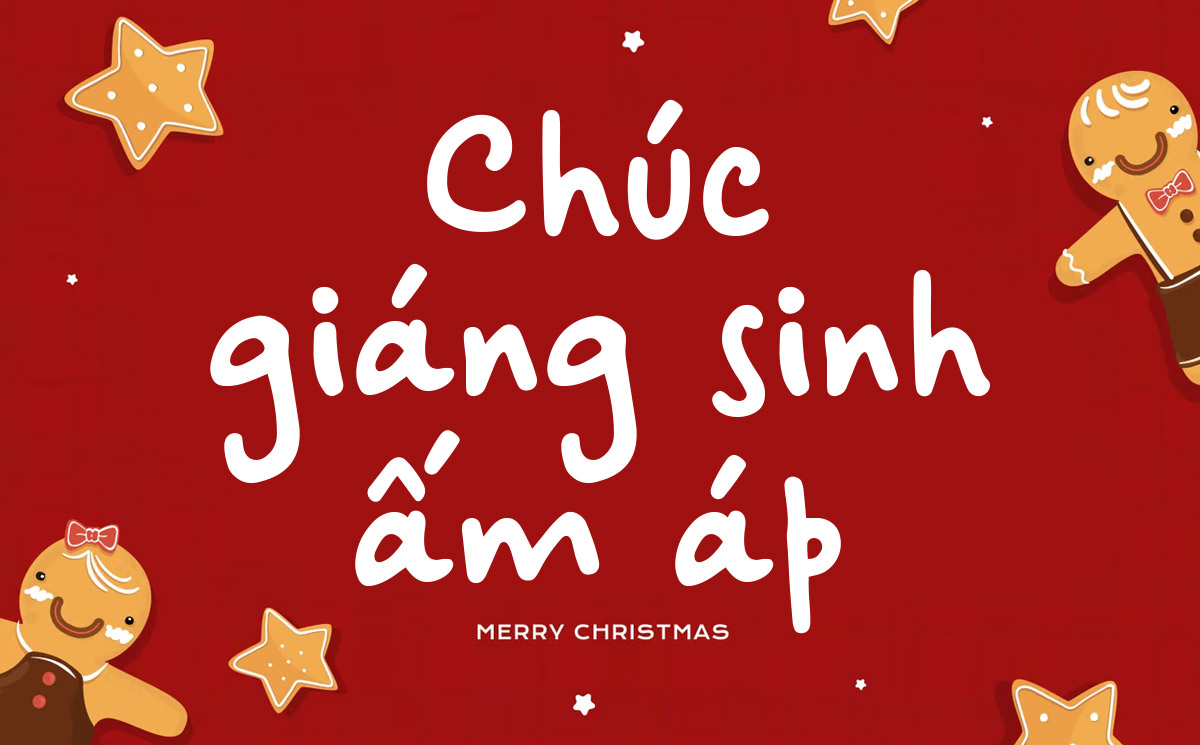
Trong thế giới thiết kế đồ họa hiện đại, việc lựa chọn font chữ phù hợp đóng vai trò quyết định đến cảm xúc và thông điệp mà thương hiệu muốn truyền tải. Font chữ cute Việt hóa SVN Be Cool là một trong những bộ font chữ kiểu viết tay vô cùng đáng yêu, mang đến làn gió mới mẻ, trẻ trung và tràn đầy năng lượng tích cực cho mọi sản phẩm thiết kế. Được Việt hóa chuẩn chỉnh, bộ phông chữ này giúp các designer dễ dàng gõ tiếng Việt có dấu mà không gặp bất kỳ sự cố lỗi font nào.
Dù bạn là một designer chuyên nghiệp, một nhà sáng tạo nội dung trên TikTok, Facebook, hay chỉ đơn giản là người yêu thích sự sáng tạo, SVN Be Cool chắc chắn sẽ trở thành một công cụ đắc lực trong kho nguyên liệu thiết kế của bạn. Hãy cùng khám phá chi tiết về bộ font chữ độc đáo này qua bài viết dưới đây.
Font Chữ Cute Việt Hóa SVN Be Cool – Giải Pháp Bứt Phá Sáng Tạo Cho Mọi Dự Án Thiết Kế
Bộ font chữ cute Việt hóa SVN Be Cool nổi bật với các đường nét phóng khoáng, tự do nhưng vẫn giữ được sự cân đối và tính thẩm mỹ cao. Không gò bó theo các quy chuẩn chữ in truyền thống cứng nhắc, SVN Be Cool mang lại cảm giác thân thiện, gần gũi và vui tươi ngay từ cái nhìn đầu tiên. Bộ phông chữ này được ứng dụng rộng rãi trong nhiều lĩnh vực khác nhau như thiết kế thiệp mừng, bìa sách thiếu nhi, bao bì sản phẩm, bảng hiệu quán cafe, cho đến các ấn phẩm truyền thông số.
Nhờ vào quá trình Việt hóa kỹ lưỡng từ nhóm tác giả SVN, toàn bộ bộ ký tự tiếng Việt với đầy đủ các dấu thanh, dấu phụ đều được tinh chỉnh tỉ mỉ. Các khoảng cách giữa các chữ cái (kerning) được tối ưu hóa nhằm mang đến sự mượt mà tuyệt đối khi gõ văn bản dài hoặc các câu slogan ấn tượng.
1. Phong Cách Nét Vẽ Hand-drawn Bo Tròn Đậm Chất Cute Và Trẻ Trung
Điểm thu hút lớn nhất của font SVN Be Cool chính là đường nét thiết kế mang đậm phong cách vẽ tay (hand-drawn). Các đầu chữ cái được xử lý bo tròn tinh tế, tạo nên vẻ ngoài mềm mại, ngộ nghĩnh và đầy tính nghệ thuật. Bộ font này tái hiện lại cảm giác chân thực của những nét bút dạ hay bút màu vẽ trên giấy, mang lại nét hồn nhiên, nhí nhảnh nhưng không kém phần hiện đại.
Sự bất quy tắc một cách cố ý trong tỷ lệ giữa các chữ cái giúp font chữ thể hiện được cá tính mạnh mẽ, phù hợp với các thiết kế hướng tới đối tượng người dùng trẻ tuổi, trẻ em, hoặc những thương hiệu muốn xây dựng hình ảnh thân thiện, dễ tiếp cận. Những đường nét mềm mại này cũng giúp giảm bớt sự căng thẳng cho thị giác, giúp người xem dễ dàng tiếp nhận thông điệp một cách tự nhiên và thoải mái nhất.
2. Việt Hóa Trọn Bộ Chuẩn Chỉnh, Không Lỗi Ký Tự Tiếng Việt
Một trong những vấn đề lớn nhất của các designer tại Việt Nam khi sử dụng các bộ font quốc tế là tình trạng lỗi dấu tiếng Việt (mất nét, lệch dấu, hoặc ký tự bị đổi thành font mặc định). SVN Be Cool đã giải quyết hoàn toàn rào cản này nhờ quá trình Việt hóa chuyên nghiệp.
- Đầy đủ dấu thanh: Các dấu huyền, sắc, hỏi, ngã, nặng cùng các dấu phụ như ă, ơ, ê, ư đều được thiết kế tỉ mỉ, đồng bộ về độ dày và phong cách với nét chữ chính.
- Hệ thống ký tự phong phú: Bộ font bao gồm đầy đủ chữ cái hoa, chữ cái thường, hệ thống chữ số rõ ràng và các ký tự đặc biệt, dấu câu thông dụng.
- Khoảng cách Kerning chuẩn xác: Tối ưu hóa khoảng cách giữa các chữ cái giúp văn bản hiển thị đẹp mắt, không bị dính nét hay đứng quá xa nhau khi gõ tiếng Việt.
3. Tính Ứng Dụng Đa Dạng Trên Nhiều Lĩnh Vực Thiết Kế
Font chữ cute Việt hóa SVN Be Cool không bị giới hạn trong một khuôn khổ nhất định mà có khả năng biến hóa linh hoạt trong nhiều loại hình ấn phẩm thiết kế khác nhau:
- Thiết kế Banner & Social Media Post: Tạo điểm nhấn thu hút cho các bài đăng trên Facebook, Instagram, banner quảng cáo khuyến mãi, hình thu nhỏ (thumbnail) YouTube hay video TikTok.
- Bao bì sản phẩm & Nhãn mác: Rất thích hợp cho các mặt hàng như bánh kẹo, đồ uống, trà sữa, mỹ phẩm thiên nhiên, đồ chơi trẻ em hay thời trang tuổi teen.Bên cạnh đó, SVN Be Cool còn là sự lựa chọn hoàn hảo để làm tiêu đề sách truyện thiếu nhi, tạp chí sáng tạo, thiết kế sticker, thiệp sinh nhật, thiệp mời sự kiện hay các câu quote cảm hứng mang phong cách vui tươi.